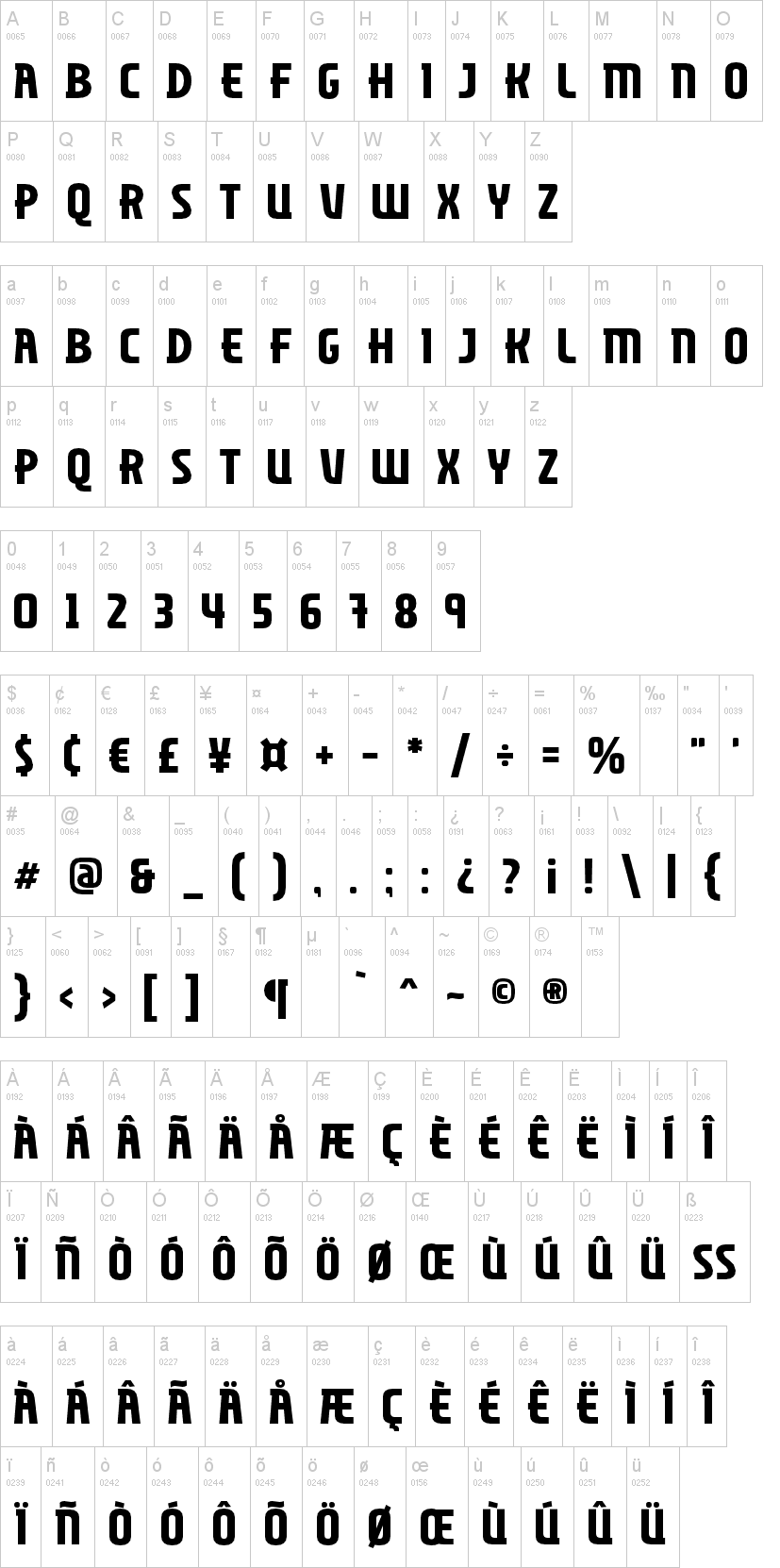
Note of the authorMiliciana es una tipografía de título, unicase, de distribución gratuita. Desarrollada durante el electivo Diseño de Fuentes Digitales (UTEM), su construcción tiene como base el trabajo letrístico del boletín "El Patriota, órgano oficial de las milicias rodriguistas"; el cual circulaba durante la dictadura militar en Chile. Tenía como función principal la entrega de información a los milicianos y a personas a fines con las ideas del Frente Patriótico Manuel Rodríguez (FPMR). Miliciana, como tipografía, rescata el ímpetu del trabajo manual, colectivo y obrero. Como referente secundario, se puede observar al muralismo y el rayado callejero. Miliciana: una tipografía incendiaria.